Hablando con Andrea, otra de mis sobris, pensamos en hacer unos letterings con mucho colorido para poner los nombres en la mesa.
Materiales para hacer un fondo de acuarela.
- Papel de acuarela (o mix media).
- Acuarelas líquidas Ecoline.
- Rotulador con punta de pincel.
- Pulverizadores.
- Tijeras.
- Agua.
Cómo hacer un fondo de acuarela de colores.
Preparar la mezcla
Para hacer nuestro fondo de acuarela vamos a usar acuarelas Ecoline. Son acuarelas líquidas y con colores muy intensos.
Como los colores de las acuarelas Ecoline se pueden mezclar nos va a ser muy fácil obtener nuestros colores.
Lo único que hay que hacer es poner un poco de acuarela líquida en un pulverizador y añadir un poco de agua hasta obtener un color más o menos intenso. Cuanto más agua añadas, menos intenso será el color.
No hace falta tener un montón de colores, puedes mezclar por ejemplo azul y amarillo y obtener el color verde.
Preparar la superficie de trabajo
Como vamos a trabajar con colores en estado líquido, es recomendable proteger la mesa o superficie de trabajo para que no se ensucie.
También te recomiendo que tengas a mano toallitas húmedas o papel de cocina 😉
A continuación, coloca el papel de acuarela sobre la mesa o en una superficie plana.
Libera tu Superpoder
Pulveriza sobre el papel la mezcla de acuarela que previamente has preparado.
Puedes usar un solo color para hacer un fondo monocromático o mezclar varios colores para hacer un fondo de acuarela multicolor como el nuestro.
Esta parte es la más divertida! Solo tienes que dar rienda suelta a tu Creatividad y liberar tu superpoder!
Trucos o recomendaciones
- Al pulverizar líquido sobre el papel, éste va absorviendo pero si echas muchas cantidad, verás como se va arrugando. No te preocupes, es normal y al secar vuelve a recuperar la forma.
- Puedes pegar el papel de acuarela a la mesa haciendo un marco con cinta de carrocero, así evitarás que se arruge al pulverizar el líquido.
- Si quieres lograr varias capas de colores sobre el papel, pulveriza un color y espera a que se seque, de lo contrario cuando pulverices el otro color se mezclará el líquido.
Cortar el papel
Una vez el papel esté completamente seco, procedemos a cortarlo.
Puedes usar unas tijeras, nosotros teníamos que hacer muchos nombres y hemos usado una guillotina.
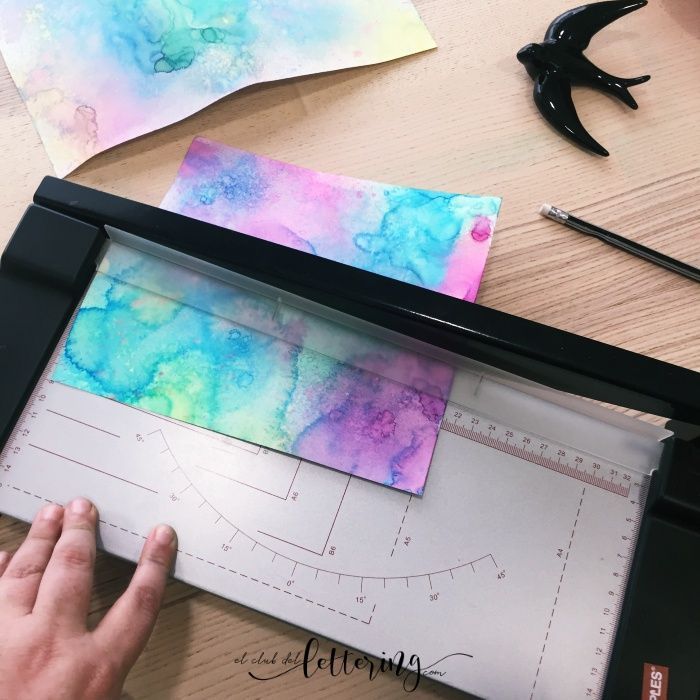
Nombres con Lettering
Una vez tenemos la base con el fondo de acuarela, con un rotulador de punta de pincel, hacemos los letterings de los nombres.
Nosotros hemos usado un rotulador Ecoline negro porque queríamos unos trazos gordos que contrastaran con el fondo de colores.
Lo que es muy importante es que cuando vayas a hacer el lettering, la acuarela esté completamente seca, de lo contrario se mezclará y pueden emborronarse las letras.
Ni qué decir tiene que esta combinación de acuarelas y lettering son la pareja perfecta y la puedes usar para cualquier cosa que pase por tu cabecita 😉